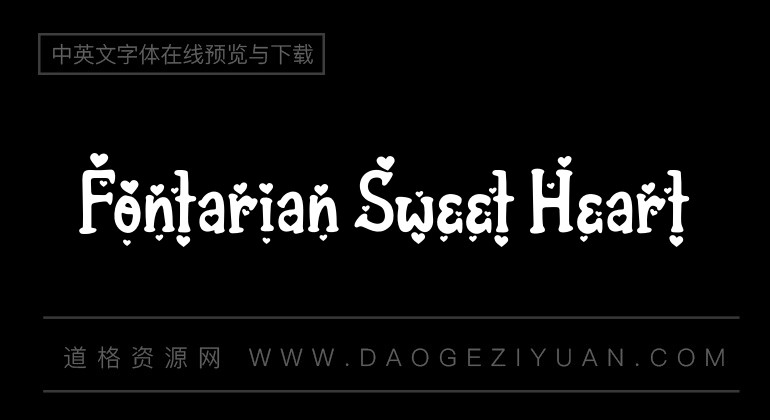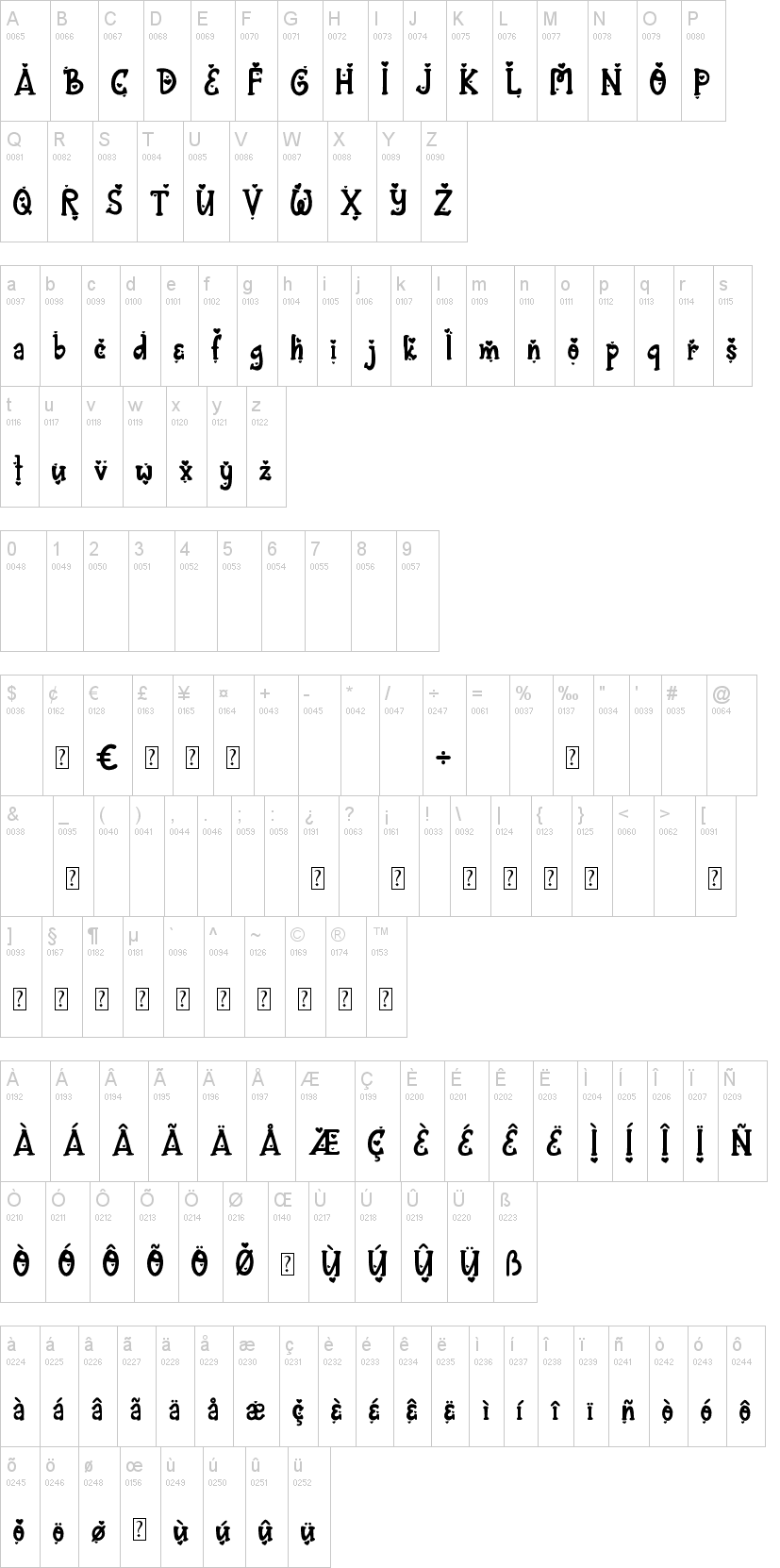
Fontarian Sweet Heart
? Fontarian Sweet Heart 字体是一款漂亮、可爱的护眼字体,它具有优雅、精致、清新的特点,它具有良好的可读性,可以让文字显得更加清晰、柔和,适合用于设计海报、封面、包装、婚礼等场景。
Fontarian Sweet Heart是一款非常不错的手写艺术字体,具有很好的视觉感,适合于文化类的宣传设计、商业类品牌的广告和产品包装设计以及个性化文字排版等较多场景。
Fontarian Sweet Heart字符映射图